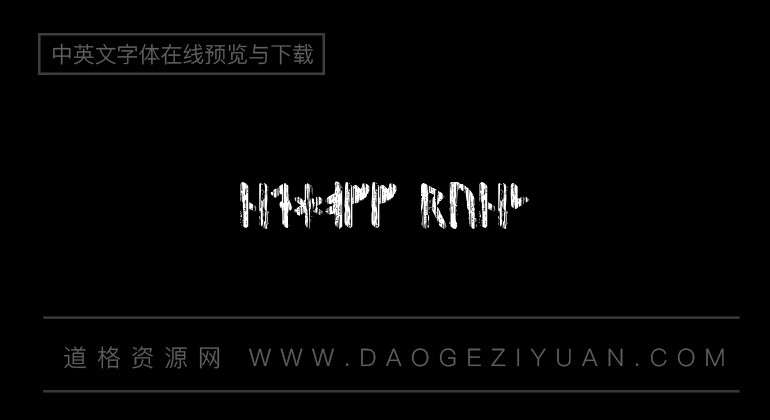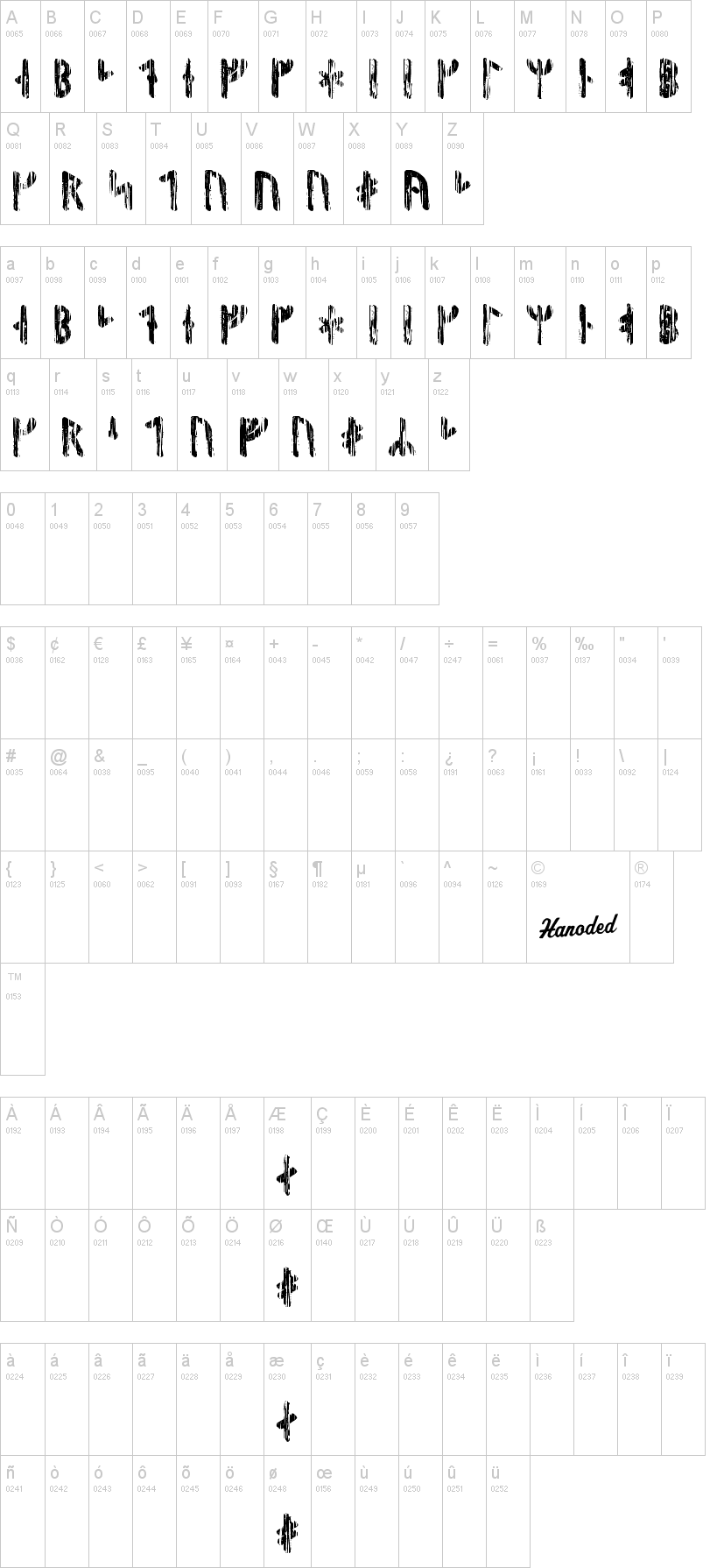
Nidhogg Runic 是一種基於北歐符文設計的字體,它是用於顯示和印刷的藝術字體。它的設計靈感來自於北歐神話中的 Nidhogg,它是一條生活在世界樹 Yggdrasil 根部的飛龍。這種字體的特點是它的字母都有尖銳的邊緣和傾斜的線條,使得它看起來很具有力量感和動感。 Nidhogg Runic 字體適用於許多不同的設計領域,如標誌和海報設計、書籍插圖、漫畫和遊戲設計等。它可以用於創造神秘、神奇、冒險和史詩般的感覺。但需要注意的是,由於其設計特點,這種字體可能不適合用於正式的商業文檔或其他需要傳達嚴肅性和正式性的場合。內容介紹
Nidhogg Runic是一款非常不錯的手寫藝術字體,具有很好的視覺感,適合於文化類的宣傳設計、商業類品牌的廣告和產品包裝設計以及個性化文字排版等較多場景。